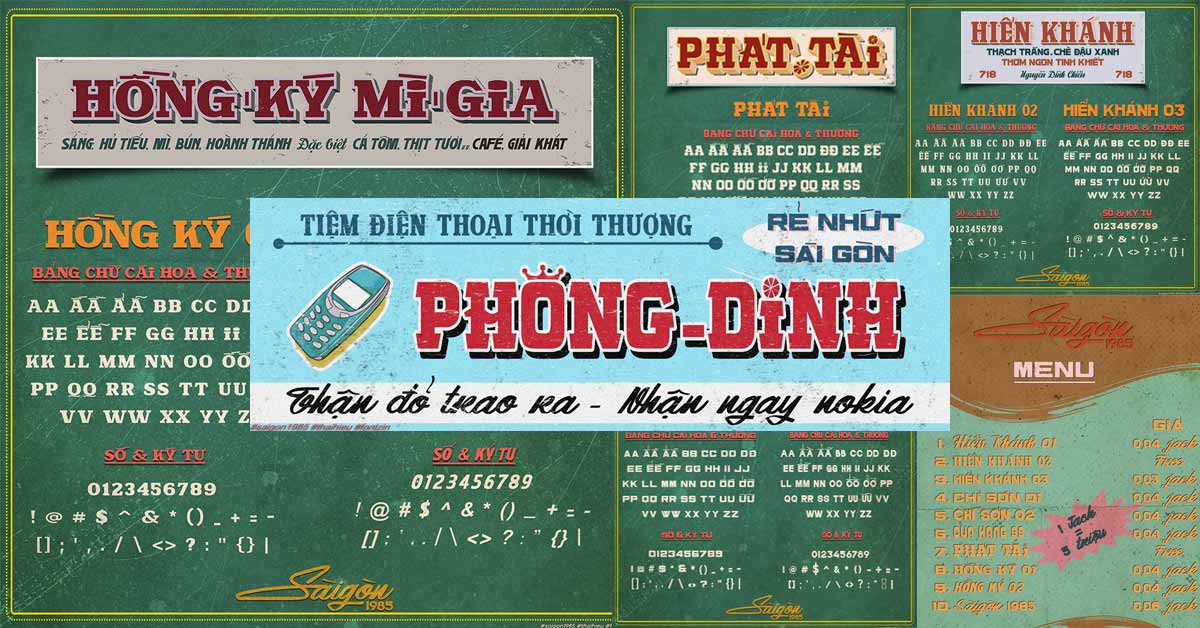
Font chữ Sài Gòn xưa Việt hóa free là nhóm các phông chữ mô phỏng lại nghệ thuật vẽ bảng hiệu thủ công tại miền Nam Việt Nam những thập niên 60 – 90. Với đặc trưng là những đường nét bút lông phóng khoáng, mộc mạc và mang đậm hơi thở thời gian, bộ font này đã trở thành lựa chọn ưu tiên cho các thiết kế bao bì thực phẩm truyền thống, quán cà phê phong cách Retro và các ấn phẩm văn hóa hoài cổ. Doozypack.vn cung cấp link tải font chữ Sài Gòn xưa chuẩn, hỗ trợ đầy đủ tiếng Việt để bạn tự do tái hiện không gian hoài niệm trên các bản thiết kế của mình.
Sức hút của font Sài Gòn xưa việt hóa trong thiết kế hiện đại
Giữa dòng chảy của các xu hướng đồ họa tối giản và hiện đại, phong cách “Sài Gòn xưa” vẫn giữ được vị thế riêng biệt nhờ khả năng kết nối cảm xúc mạnh mẽ với khách hàng thông qua thị giác.
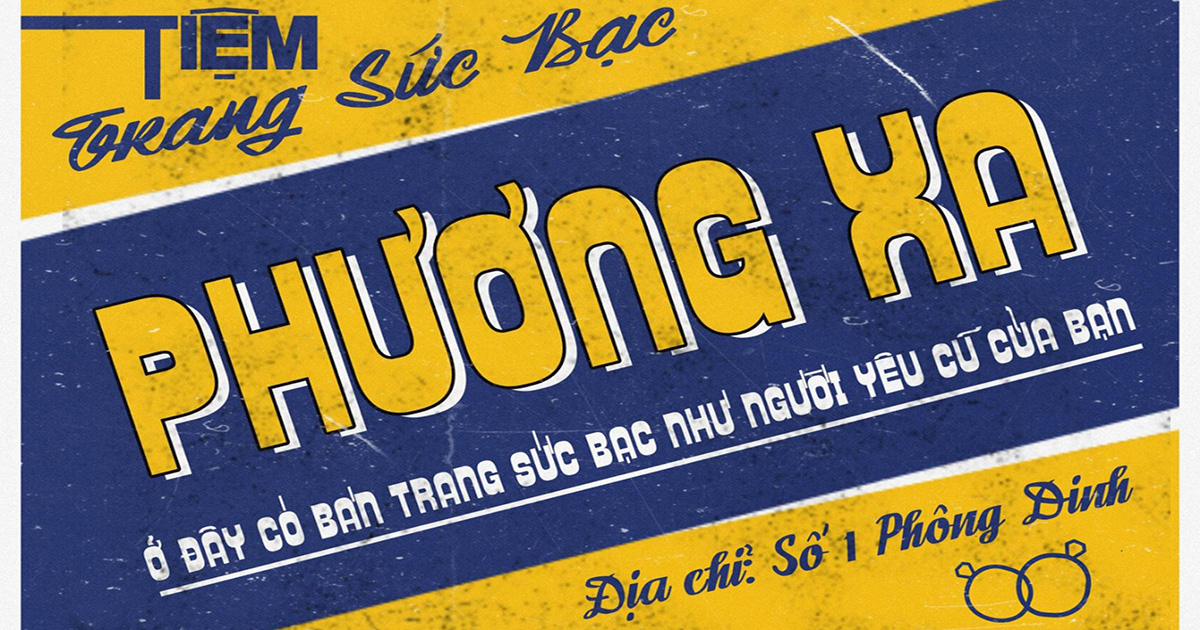
Tái hiện nét đẹp văn hóa bảng hiệu vẽ tay
Đặc trưng lớn nhất của font chữ Sài Gòn xưa việt hóa là cấu trúc nét chữ không hoàn hảo một cách có tính toán. Nó mô phỏng lại áp lực của ngọn bút lông trên nền gỗ hoặc tôn, với những đoạn chuyển nét hơi rung, độ dày mỏng biến thiên linh hoạt. Khi ứng dụng vào thiết kế logo hoặc bao bì, bộ font này ngay lập tức tạo ra cảm giác về một thương hiệu lâu đời, uy tín và đậm chất thủ công tinh tế.
Khơi gợi ký ức và sự tin tưởng từ khách hàng
Màu sắc và kiểu chữ hoài cổ luôn có sức mạnh khơi gợi ký ức. Một chiếc túi giấy hay hộp trà sử dụng font chữ Sài Gòn xưa free giúp khách hàng liên tưởng đến những giá trị truyền thống “cha truyền con nối”. Điều này đặc biệt hiệu quả trong việc xây dựng niềm tin cho các thương hiệu nông sản, bánh mứt thực phẩm hoặc các tiệm may đo thiết kế mang phong cách cổ điển.
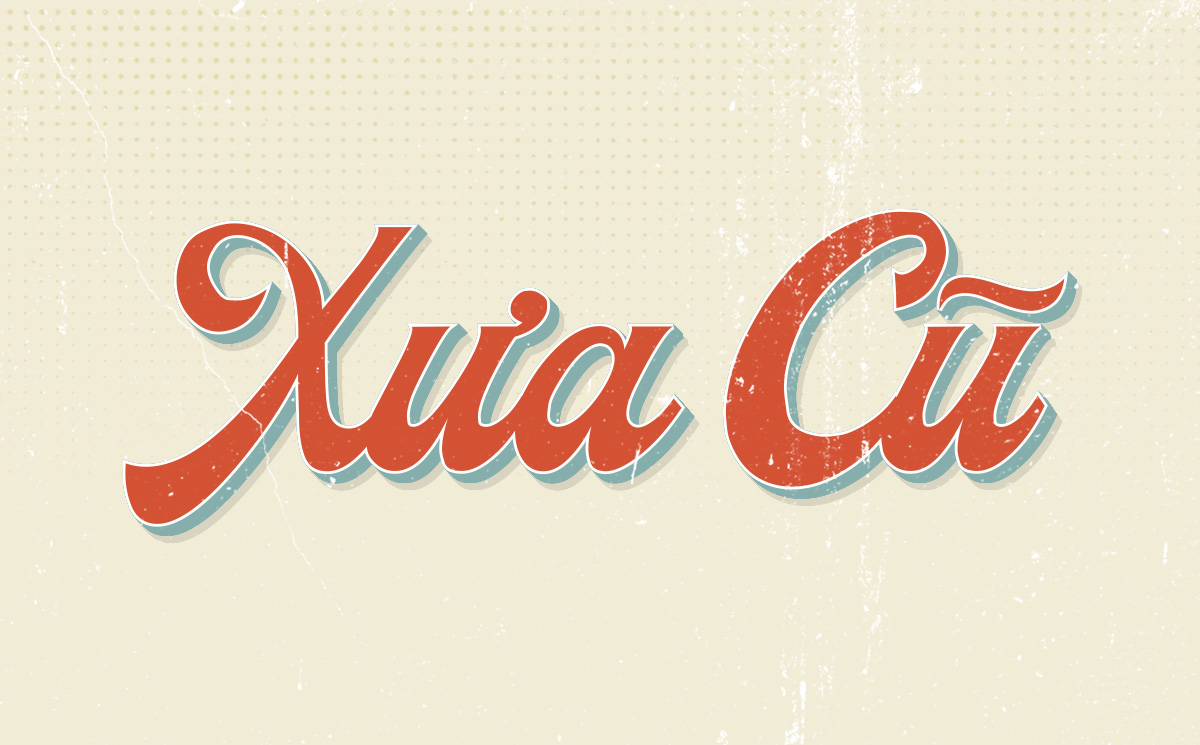
| Nhóm Font | Đặc điểm thị giác | Ứng dụng đề xuất tại Doozypack.vn |
| Font Bảng Hiệu (Signboard) | Nét dày, vững chãi, dứt khoát | Thiết kế tiêu đề hộp quà, biển hiệu quán cà phê, poster. |
| Font Brush (Bút lông) | Nghệ thuật, có độ xước tự nhiên | Dùng cho tiêu đề nhãn chai rượu, bao lì xì Tết, thiệp mời. |
| Font Retro Serif | Có chân cổ điển, trang trọng | Làm bảng thành phần, nội dung mô tả trên hộp trà, cafe. |
03 Ứng dụng của phông chữ hoài cổ trong sản xuất bao bì tại Doozypack.vn
Vẻ đẹp vượt thời gian của nhóm font này mang lại hiệu quả thị giác đặc biệt trên các ấn phẩm thực tế do Doozypack.vn sản xuất:
- Hộp giấy đựng Cà phê & Trà: Sử dụng font bảng hiệu xưa kết hợp với kỹ thuật in Offset trên giấy Ivory cán màng mờ giúp bao bì toát lên vẻ đậm đà, truyền thống.
- Túi giấy cho tiệm thời trang: Tên cửa hàng in bằng font chữ hoài cổ giúp khách hàng cảm nhận được gu thẩm mỹ tinh tế và sự tỉ mỉ của chủ thương hiệu.
- Tem nhãn sản phẩm Handmade: Rất phù hợp làm tên thương hiệu trên nhãn dán hũ mứt, tinh dầu hoặc thực phẩm đóng gói thủ công, tạo cảm giác an toàn và tự nhiên.
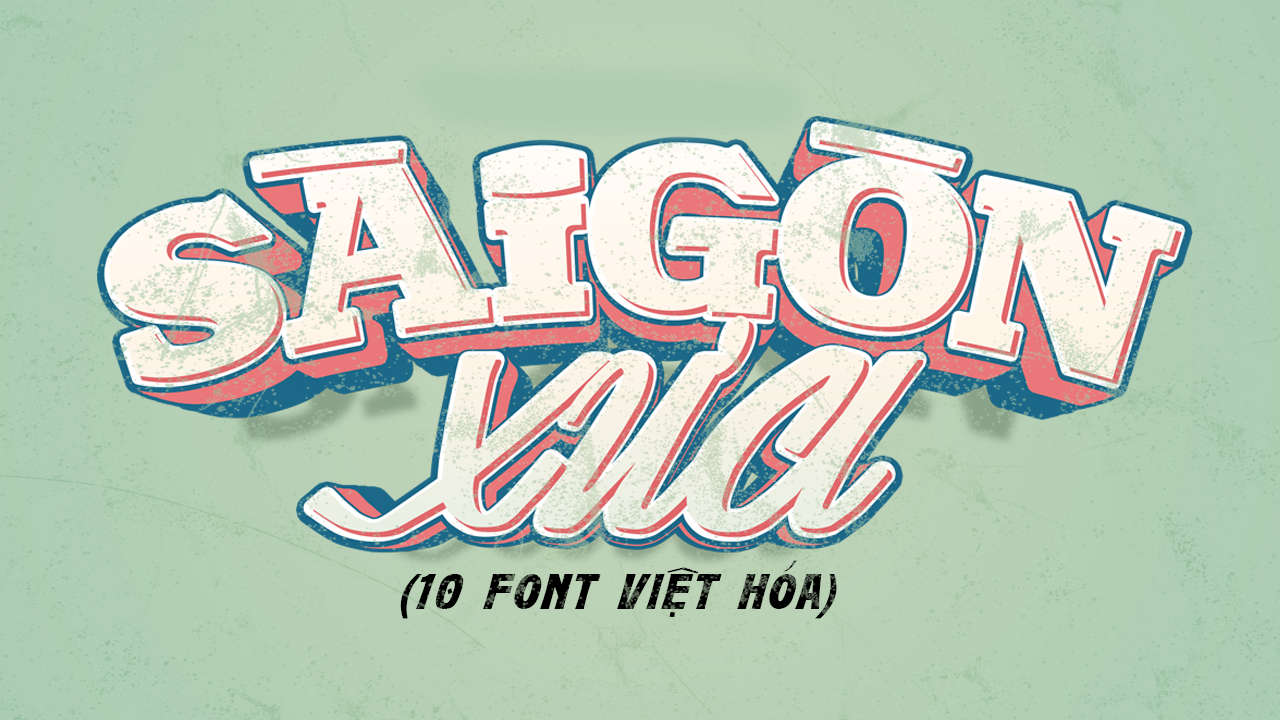
03 Lưu ý kỹ thuật khi in ấn font chữ Sài Gòn xưa
Việc đưa một phông chữ có nhiều chi tiết “thủ công” lên chất liệu giấy đòi hỏi designer cần lưu ý một số vấn đề kỹ thuật tại xưởng in chuyên nghiệp của Doozypack.vn:
- Hệ màu CMYK tông Sepia: Để có màu “retro” chuẩn, bạn nên phối màu dựa trên hệ CMYK với các tông vàng đất, đỏ đô hoặc nâu đen. Tránh sử dụng các màu Neon quá tươi sẽ làm mất đi cái “hồn” của bộ font xưa.
- Xử lý các nét xước mực: Nhiều bộ font chữ Sài Gòn xưa việt hóa có hiệu ứng xước tự nhiên. Khi in kích thước nhỏ (dưới 8pt) trên giấy nhám, các nét này có thể bị bít mực. Doozypack.vn khuyên bạn nên để tiêu đề đủ lớn để bảo đảm độ sắc nét.
- Quy tắc Convert Font: Để bản in đạt độ sắc nét tuyệt đối và không lỗi dấu, hãy luôn thực hiện lệnh Create Outlines (Ctrl+Shift+O) trước khi gửi file PDF cuối cùng cho xưởng in.
Doozypack.vn không chỉ cung cấp tài nguyên thiết kế miễn phí mà còn đồng hành cùng doanh nghiệp trong sản xuất hộp giấy, túi giấy và tem nhãn theo yêu cầu. Với những thiết kế mang đậm dấu ấn văn hóa như font Sài Gòn xưa, đội ngũ kỹ thuật chú trọng cách thể hiện từng đường nét trên chất liệu giấy, đảm bảo phần chữ giữ được vẻ hoài niệm, sắc nét và hài hòa với tổng thể bao bì. Bạn có thể tham khảo dịch vụ in hộp giấy theo yêu cầu hoặc túi giấy in logo để hoàn thiện thiết kế theo phong cách riêng.